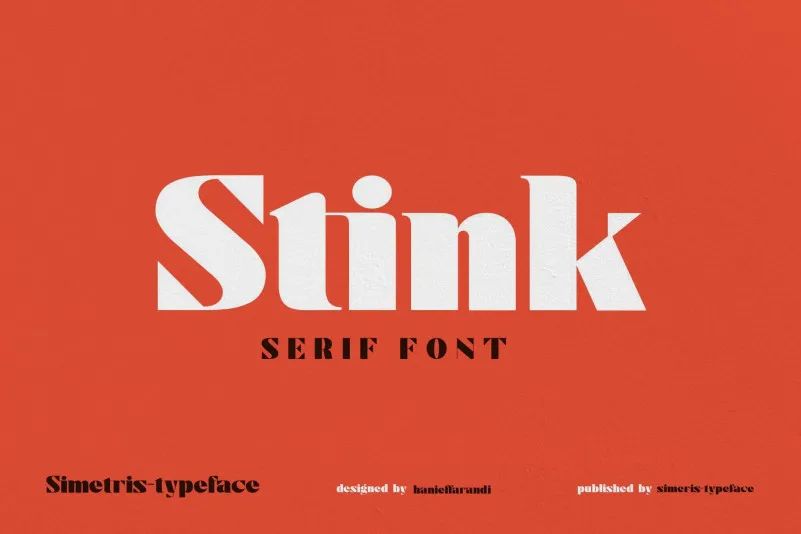
A fonte Stink é uma Serif que oferece um toque moderno e inovador, revivendo clássicos retro com força e estilo. Para quem busca a essência clássica dos typewriters mas com uma cara atual, esta é a escolha perfeita. Ideal para criar uma impressão duradoura em qualquer projeto, desde as peças de merchandising até os anúncios publicitários e designs de logo. Estamos certos de que o Stink será um elemento crucial no seu próximo design gráfico, com sua combinação única de modernidade e robustez que tornará a identificação visível em qualquer formato. Engajante para designers, este é um novo padrão que vale a pena experimentar.